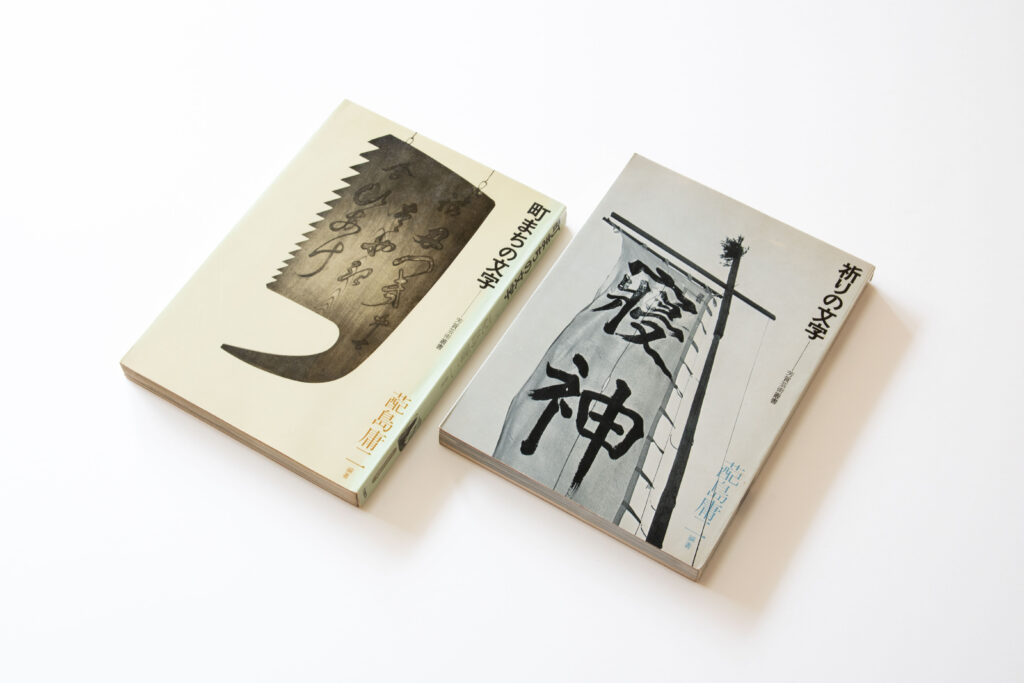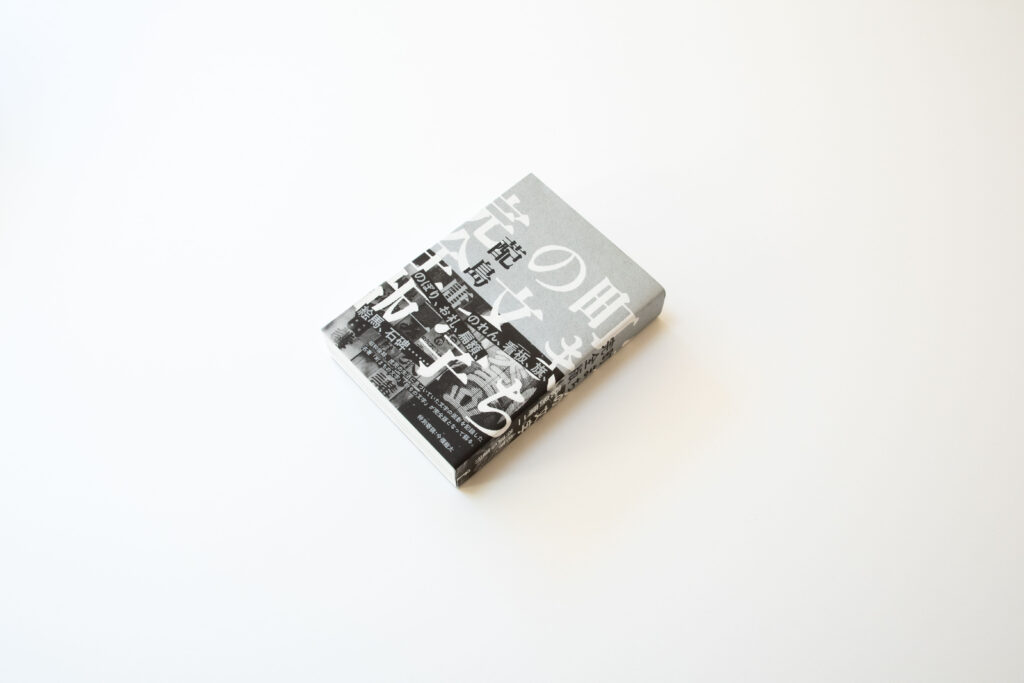
TPの書庫から『祈りの文字』『町まちの文字』
今回は、蓜島庸二著の『町まちの文字』と『祈りの文字』を紹介します。 『町まちの文字』は看板や暖簾、『祈りの文字』は扁額やお札など、たくさんの写真と共に筆者やその知人が訪ねた文字が紹介された本です。
『町まちの文字』『祈りの文字』を合冊・再編集した『町まちの文字 完全版』もあります。
『町まちの文字』は「ちょうちん屋復権ー序にかえてー」というテキストから始まりました。書道で一気に筆を運ばずなぞり書きすることを、江戸時代からの提灯・看板屋になぞらえて「ちょうちん屋」と呼び、著者は「ちょうちん屋」をすると学校の先生から叱られたそうです。なるほど、フォントの一文字一文字を直し直し作っている私は日々ちょうちん屋をしています、とちょっとした親近感が湧きました。しかし読み進めるにつれ、フォント(活字)と本書で紹介されている文字は、とても対照的なものにも思えてきます。活字は組み換えていろいろな文章に使えるよう汎用的にデザインされるのに対し、この町々の文字と祈りの文字の多くはその書かれた場所のために用意された特別な文字なのです。
筆者の感性・体験・知識とともにそれぞれの文字を読み解いていくと、たった数文字を写した写真にも多くの情報が内包されていました。写真の多い本だと気楽に構えていたのに読了まで予想以上の時間がかかってしまいましたが、嬉しい誤算であったと感じます。
『町まちの文字』
著者:蓜島庸二
発行:芳賀書店
『祈りの文字』
著者:蓜島庸二
発行:芳賀書店
『町まちの文字』『祈りの文字』を合冊・再編集した『町まちの文字 完全版』もあります。
『町まちの文字 完全版』
著者:蓜島庸二
発行:グラフィック社